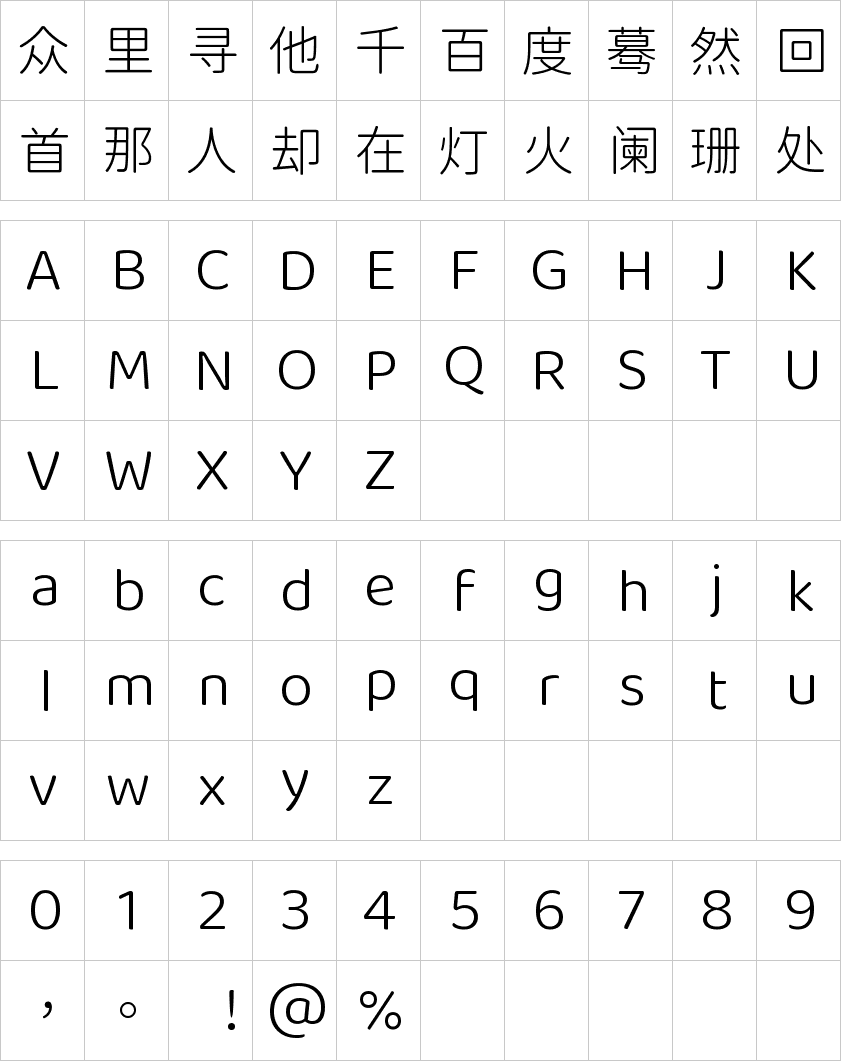
江城圆体
被设计耽误的程序大神刘鹏,基于源泉圆体进行改造,把一些台湾习惯的字形进行简体化修正,发布了一款比较适合我们大陆设计师使用的字体”江城圆体“。这款字体基本源泉圆体改造,所以简体也是不缺少字的。并且有6个字重,十分贴心。猫啃网建议大陆的设计师们,可以把电脑上的源泉圆体删掉,替换成这款江城圆体吧!!江城圆体改过的字可以点击这里查看。